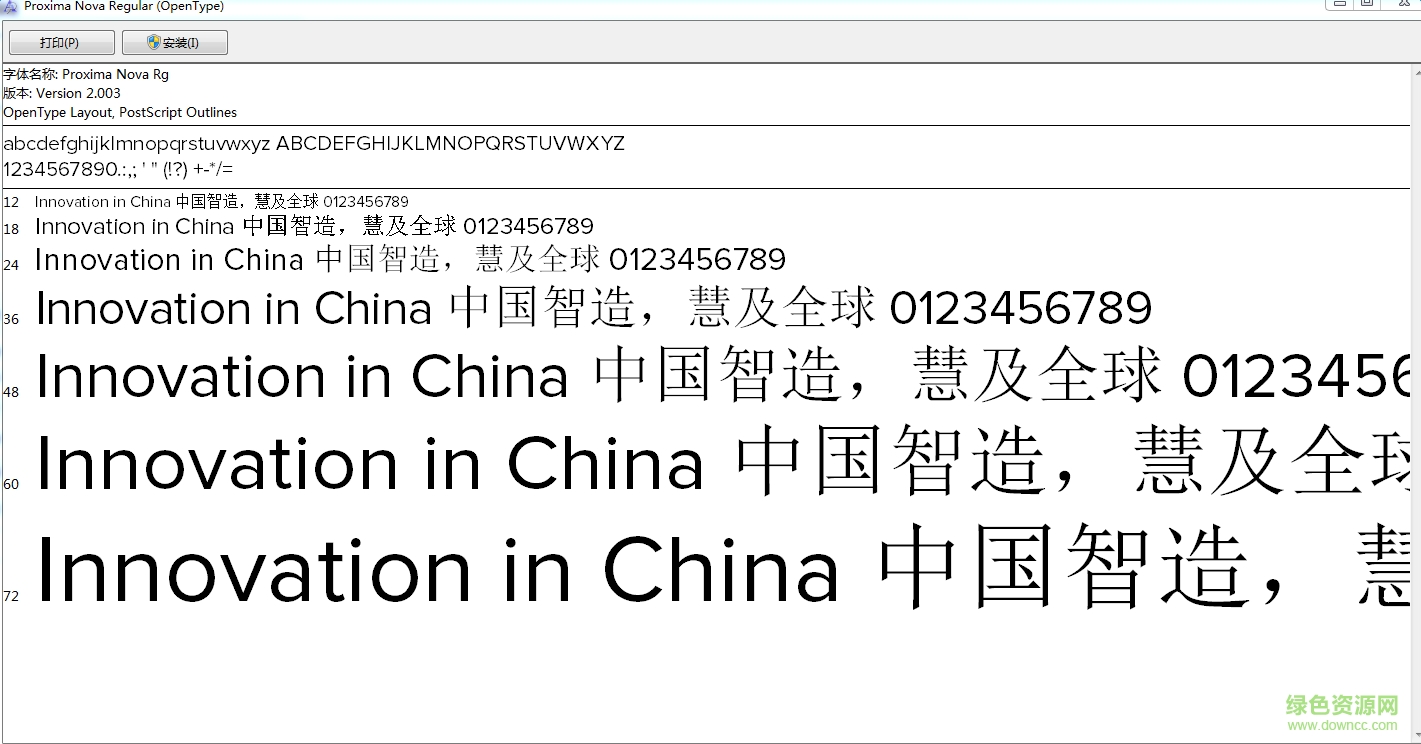
proxima nova regular字體是一款實用性強的英文字體,該字體筆畫流暢,點畫得宜,結構嚴謹卻又不乏親和力,喜歡的朋友不妨下載試試!
Proxima有些特別獨特的韻味,現(xiàn)代而又不冰冷。尤其是它的代表性的小寫“a”很有味道。Proxima nova是我經(jīng)常使用的字體之一。